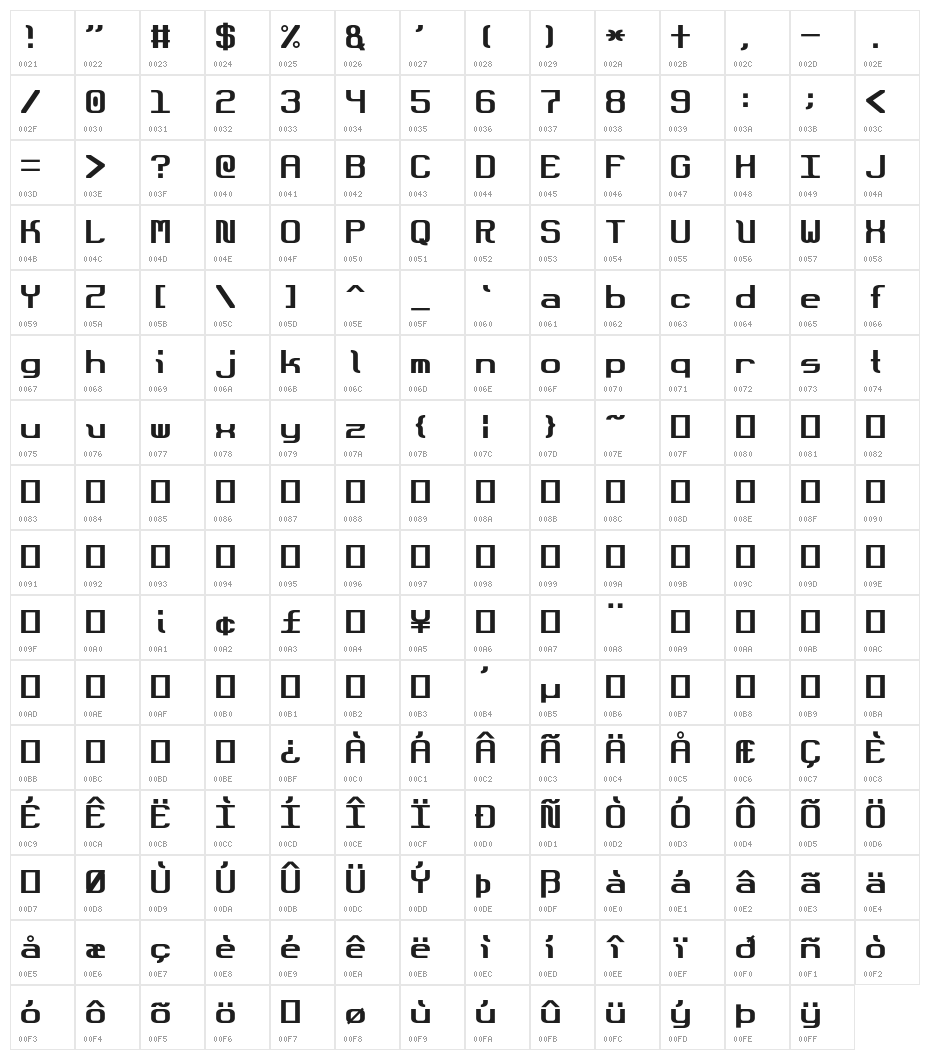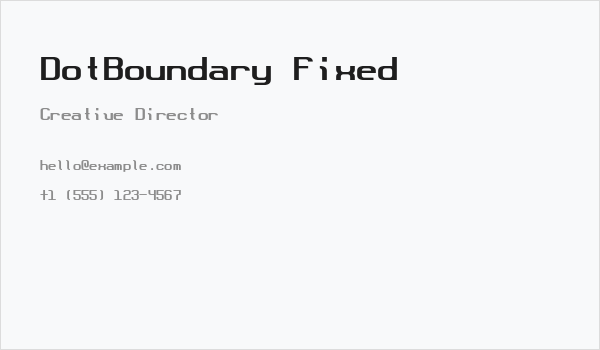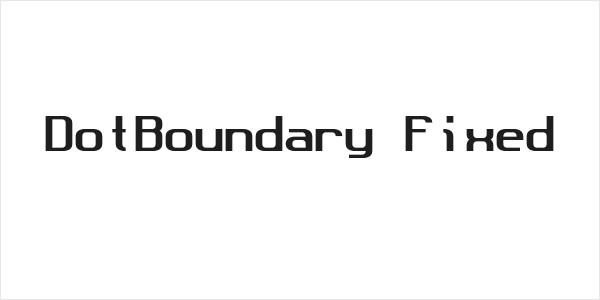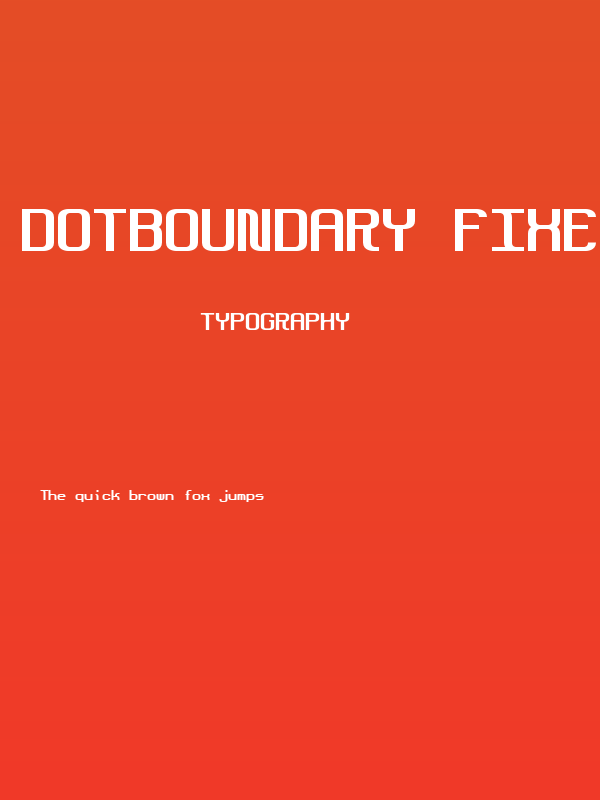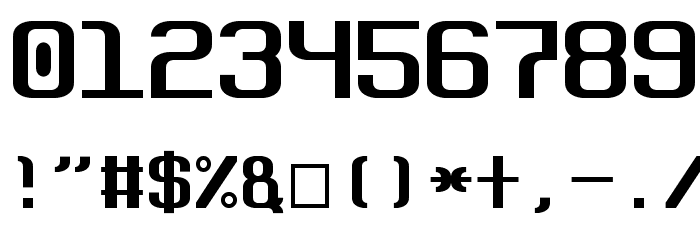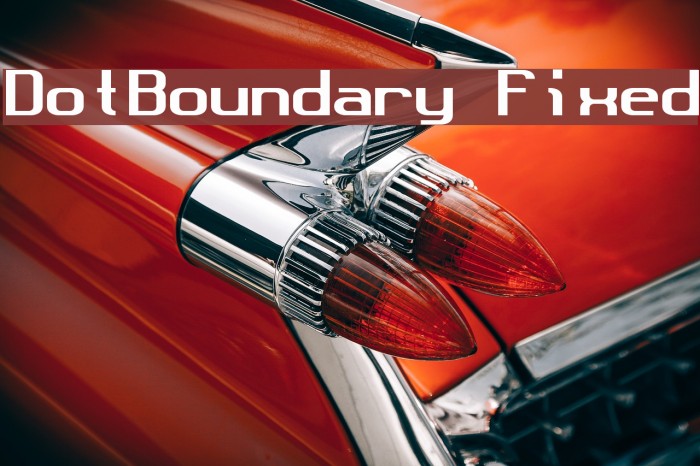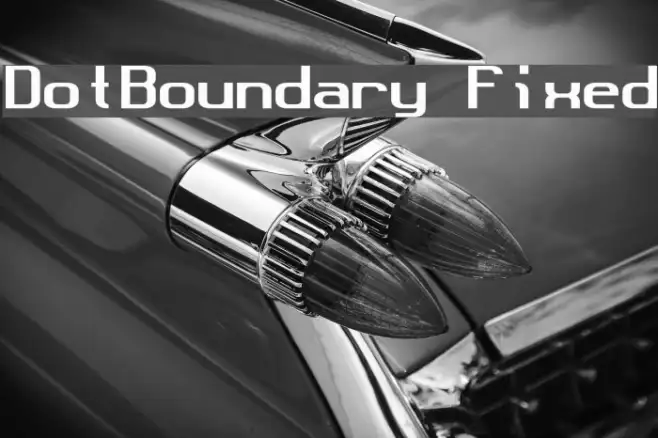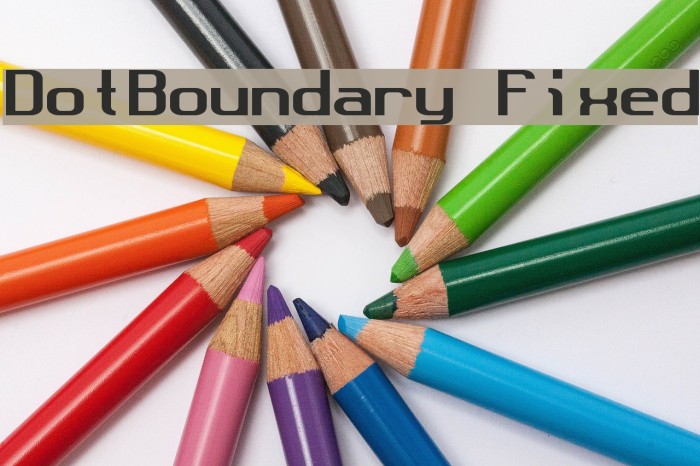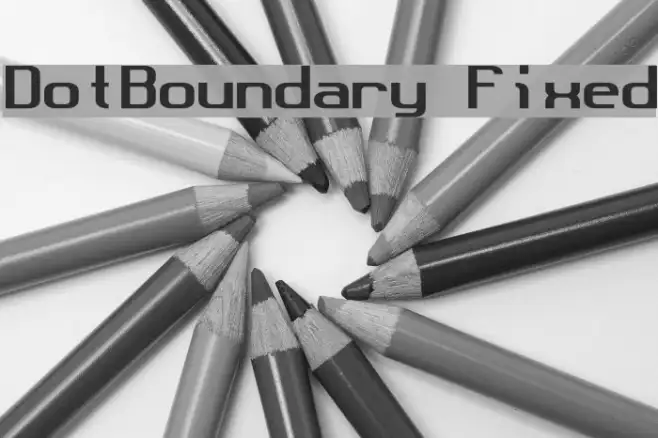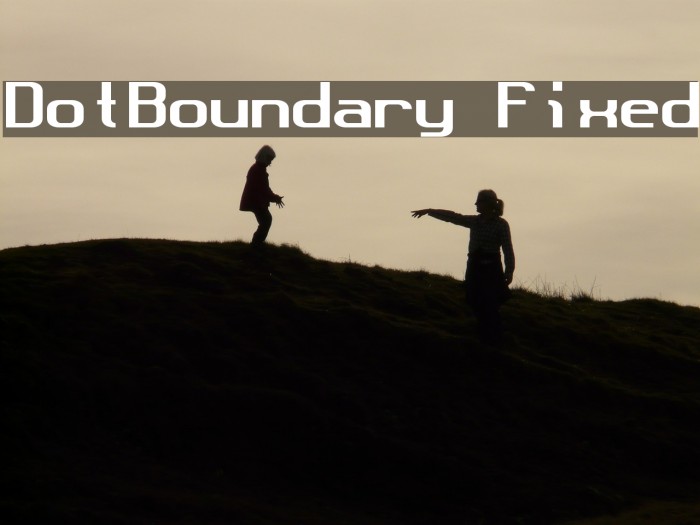
DotBoundary Fixed Font
Esta fuente incluye 257 caracteres. Haz clic en cualquier carácter para ver los detalles.
| Caso de uso | Digital displays, Technical documents, Coding environments |
| Proyectos propuestos | Ideal for coding environments, technical documentation, digital interfaces, and modern branding projects. |